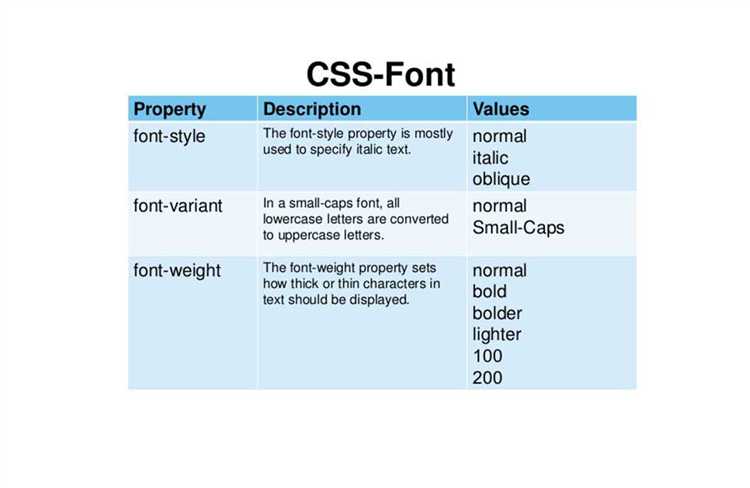
Как сделать не жирный шрифт css
Свойство font-weight в CSS отвечает за толщину шрифта. По умолчанию, большинство шрифтов имеют стандартный вес (обычно 400), но иногда необходимо отклониться от этой нормы и изменить жирность текста. Когда шрифт выглядит слишком жирным, это может отвлекать внимание читателя или нарушать визуальную гармонию страницы. Чтобы сделать текст не жирным, CSS предлагает несколько вариантов настройки данного свойства.
Для того чтобы избавиться от жирности, можно использовать значение normal, которое является стандартным значением для большинства шрифтов. Оно отменяет любое усиление веса шрифта, установив его на стандартный уровень. Пример использования:
p {
font-weight: normal;
}
Если шрифт по умолчанию уже не является жирным, но вы столкнулись с проблемой того, что текст выглядит толще, чем хотелось бы, убедитесь, что не применены дополнительные стили, например, bold или bolder. Также важно помнить, что не все шрифты поддерживают изменения веса, и в таких случаях они могут не давать ожидаемого результата при изменении font-weight.
Для более точной настройки шрифта важно знать, какой именно вес поддерживает шрифт. Если шрифт позволяет задать несколько уровней толщины (например, 100, 200, 300 и т.д.), можно использовать соответствующие значения для более детальной настройки, но normal останется самым простым и универсальным решением для большинства случаев.
Определение жирности шрифта через свойство font-weight
Свойство font-weight в CSS используется для задания толщины символов текста. Оно принимает несколько значений, от числовых (100-900) до ключевых слов, таких как normal и bold.
Основные значения:
• normal – стандартная жирность, обычно 400. Это значение используется по умолчанию.
• bold – задаёт жирность, эквивалентную 700.
• Числовые значения – от 100 до 900. Меньшие значения делают шрифт тоньше, большие – толще. Каждый шаг соответствует увеличению толщины шрифта. Примеры: font-weight: 200; или font-weight: 600;.
Некоторые шрифты поддерживают только несколько вариантов толщины, например, только normal и bold. В таких случаях, если указано значение, которое не поддерживается, браузер может подставить ближайшее доступное.
Если цель – сделать шрифт не жирным, можно использовать значение font-weight: normal;, которое является дефолтным и эквивалентно 400.
Для более точной настройки можно использовать промежуточные значения, например, font-weight: 300; для менее жирного текста или font-weight: 500; для средней толщины.
Важно помнить, что свойство font-weight не всегда будет работать для всех шрифтов, так как некоторые из них могут не иметь всех промежуточных значений, что зависит от их дизайна и стилей, предусмотренных в файле шрифта.
Как установить нормальную толщину шрифта с помощью значения «normal»
Чтобы задать стандартную толщину шрифта в CSS, используют значение «normal» для свойства font-weight. Это значение указывает на обычную, стандартную плотность шрифта, которая отличается от жирного (значение bold) или тонкого (значение lighter) шрифта.
Использование font-weight: normal; позволяет браузеру применить толщину, которая соответствует нормальному весу шрифта, заданному по умолчанию. Это часто используется, когда необходимо отменить другие стили или вернуть шрифт к стандартному виду после применения более жирного или тонкого начертания.
Пример CSS-правила, устанавливающего нормальный вес шрифта:
p {
font-weight: normal;
}
Значение «normal» является эквивалентом числового значения 400. Если в вашем проекте используются разные шрифты, важно помнить, что толщина шрифта по умолчанию может варьироваться в зависимости от выбранного семейства шрифтов, так как не все шрифты поддерживают одинаковые веса.
Использование font-weight: normal; также помогает сохранить совместимость с различными шрифтами, не нарушая их внешний вид. Это особенно важно при работе с веб-шрифтами, где часто требуется обеспечить минимальное вмешательство в оригинальные настройки шрифта.
Использование числовых значений для контроля жирности шрифта
Для точного управления жирностью шрифта в CSS можно использовать числовые значения, которые задаются через свойство font-weight. Вместо использования предустановленных ключевых слов, таких как normal или bold, вы можете использовать числовые значения от 100 до 900. Эти значения позволяют более гибко контролировать толщину текста и дают возможность точно настроить визуальный стиль шрифта.
Числовые значения для font-weight представляют собой шкалу, где 400 соответствует обычному (нормальному) шрифту, а 700 – жирному. Однако стоит помнить, что для некоторых шрифтов диапазон доступных значений может быть ограничен. Например, шрифт, который поддерживает только два веса, будет корректно отображаться только для значений 400 (обычный) и 700 (жирный).